訪問當天,冬日放晴回暖,許瀚文心情歡快,他在月初發表的「空明朝體」羣眾集資計劃,募得款項剛好突破一千萬台幣(最新數字為一千二百五十多萬台幣,約四百萬港元),遠超原訂目標四百萬台幣。能夠得到港台兩地踴躍支持,他喜出望外,「雖然自己很用心造這套字體產品,但沒料到反響這麼大。十多年前,我剛入行時,字體相關的,講什麼都沒人理會,沒人有idea。」說時,他臉上有成就了大事的滿足感,「做到這個成績,真是很開心,也很讚嘆香港台灣對美學的認同。」
作為字體設計師,他希望藉着自己構思的「空明朝體」,帶出與別不同、空氣流動、如同呼吸般舒適的閱讀感覺。「自己母語的地方,繁體中文的地方,deserve有這種新的感受。如果我要幫這個地方的文化做improvement,這就是我能付出的一部分。」
走進字的美學世界
許瀚文是左撇子。寫字之於他從來都是「不自然」的。中文的字形結構屬「右手美學」,寫法為「左收右放」,以右手寫字較順筆勢;反之左手寫字,「永遠似是畫公仔」,他卻領略到好處,「這讓我可以第三身去analyse那些字。」
少時,他確實喜歡「畫公仔」,想過選修視藝,但中學老師說他沒有天分,把他勸退。不過,他對美術的興趣分毫不減,更想在大學修讀設計。此路不通,那便另闢蹊徑,於是再回到了字。他發現,透過操作簡易的Flash CS4軟件,舞弄字體幾下,已可得出吸引人的
視覺效果,讓人看見字體之美,自此眼界大開。「那時已知道(字的)visual impacts很大,」他說,「不需要畫底好強才能做到吸引人的東西,字體已經可以。」
中學畢業之際,他就是帶着自學Flash試造的多份字體作品,到理工大學設計學院面試,幸獲取錄。「自此全部時間放在排版、字體等。畫graphic、剪片,應付了就算。」大學三年班,他上了中文字體設計大師柯熾堅的課,畢業初出茅廬,就是當柯熾堅的學徒,助他開發全新的「信黑體」。
「學了三年,由最基本學起,學怎樣畫鈎。」許瀚文回憶,當時經驗尚淺,自己幫到的有限,反而受益甚多,特別是如何下一個設計決定。「(柯熾堅)他的看法很厲害,一針見血。這個不夠美,為何不美?什麼是中文字的堅持?哪些是中文字需要的,日文字不需要的?他都能清楚講解。」滿師後的他,也能充滿自信地向客人說明每個字型設計背後的理據。
造字學無止境
學徒可以期滿,但造字這門學問,則學無止境,造字人需要耐性,在字的直線曲線無窮變化組合中,不斷摸索美感。「你要手和眼都要synchronise才會做到,是非常細緻的。」捉緊了美感,如何把感覺呈現,也是工夫。「是一個很抽象的過程,但你又要令它具象。(造字)不是純粹工藝,都是很多設計思維在背後,兩件事綜合。」許瀚文形容。
這些字體設計的理解,也是他邊做邊學所得的體會。他先後在英國Dalton Magg、美國Monotype等字體公司任職字體設計師,不同的地方環境,刺激他不斷思考前進。他難忘在二〇一二至一四年在倫敦工作的時光。「好正。學到很多關於線條或人性的appreciation。」
這段經歷對他影響深遠,「英國的字體與其他世界各地造的英文字體很不同,他們強調線條的溫柔、柔美,字體(呈現)出來要welcoming的、不會太aggressive的。這方面很inspire我:字是給人看的,人們看到應該要是舒服的。」
後來他進了Monotype香港分部,參與更多如騰訊、《紐約時報中文版》和《彭博商業周刊中文版》等大企業的商標字體設計;也曾加入日本著名字體設計師小林章的團隊成員,和其他日本設計師合作,他專責漢字部分。「在那真的學到整個程序,接觸層面廣,但那陣子經常被迫到大陸工作,我不太喜歡,就辭職了。」
為了更美好的中文字
工作經驗加上自己的文化觀察,讓許瀚文開始留意到香港甚或中文字體文化之不足。「英國人、日本人,他們都對字體有感受,但中文(文化圈),我每次問到,都答沒有感受。」
為什麼?他認為,現存的中文字體大多枯燥單調,不分媒介內容性質,來來去去,總是用那幾套字體。歸根究柢是選擇太少,有的字型更與中文美學脫離,或不足以應付各種可能情況,因此許多港台設計師常借用日文字型排版創作。
「在日本、英國,他們有各自適用的字體。有書籍專用的字體,感覺會較柔、詩意、舒服;新聞用的就較清脆硬朗。」仰望外地的字體風景,許瀚文也想像本地可以這樣。二〇一四年,他構思出一套名為「空明朝體」的明體字型,希望它能易讀秀麗,具備中文字應有的美,並且真正與人們自小就培養的文字審美觀相接,革新中文閱讀感受。
六年間,他研究實驗,幾經修正,與港台兩地設計師多番合作,終於慢慢琢磨出「空明朝體」的基礎輪廓。
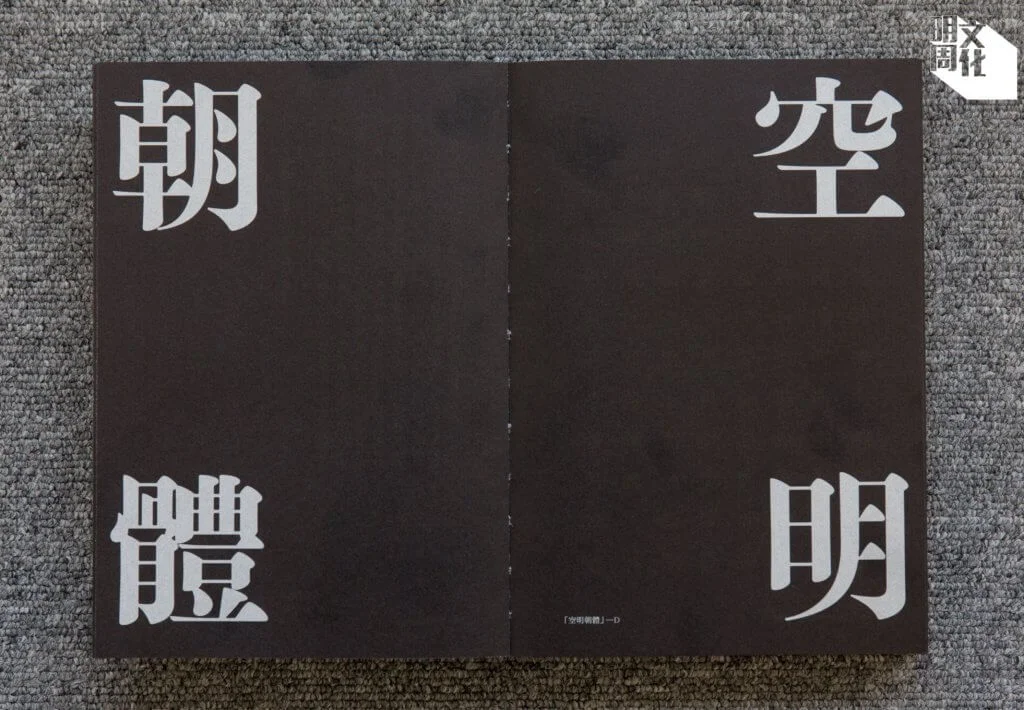
樽頸過後的轉機
然而,許瀚文久久未有將「空明朝體」投入完整生產,補完所有中文基本通用字,讓「空明朝體」可以真正用作正文排版的計劃—直到去年六月。
去年初,他憑着一八年贏得的「DFA 香港青年設計才俊獎」獎學金,到德國設計公司KMS TEAM實習。他離開香港,遠赴慕尼黑的時間,正處於事業的瓶頸。「在這一行,自己不算最後生,作品又不算是最新最fresh的,講老又不夠老資格。雖然做的事很多時近type director的位置,但又未到那個時候。」三十來歲的他,努力十年,漸感迷惘,「夾了在中間,不上不下,所以想試試其他可能性。」
一心想在德國深造,不幸當地爆發疫情,自去年三月起,政府下令封城禁足。實習工作驟然停頓,安困愁城也沒意思,許瀚文意興闌珊,決定返港。這反而帶給他新的轉機。
回港後,聞說昔日共事過、造字資歷逾三十年的造字匠人張堅強和馮景祥,因為Monotype香港分部停業而突然失去工作,「他們一直是中流砥柱,做了很多年,不想他們轉行,失去他們」,因此許瀚文試問兩位前輩:有沒有興趣一起完成整套「空明朝體」?
他不諱言,自己一直未有實現「空明朝體」的構想,是因為自己眼高手低,經驗不足,始終無法把字造得「工整得來,又是活的」;若得兩位造字經驗老到的師傅幫手,定必能夠把「空明朝體」完成。「果然,他們搞了兩個月,事情已經和我想像的一樣,到我最滿意的程度」,他特別感謝張堅強,「阿堅研究書法廿幾年,他可以帶字的氣韻章法等到這套字體。」
「我有idea,然後配合他們的craft,事情就完美了。」他成功突破了瓶頸,找到新的路向。
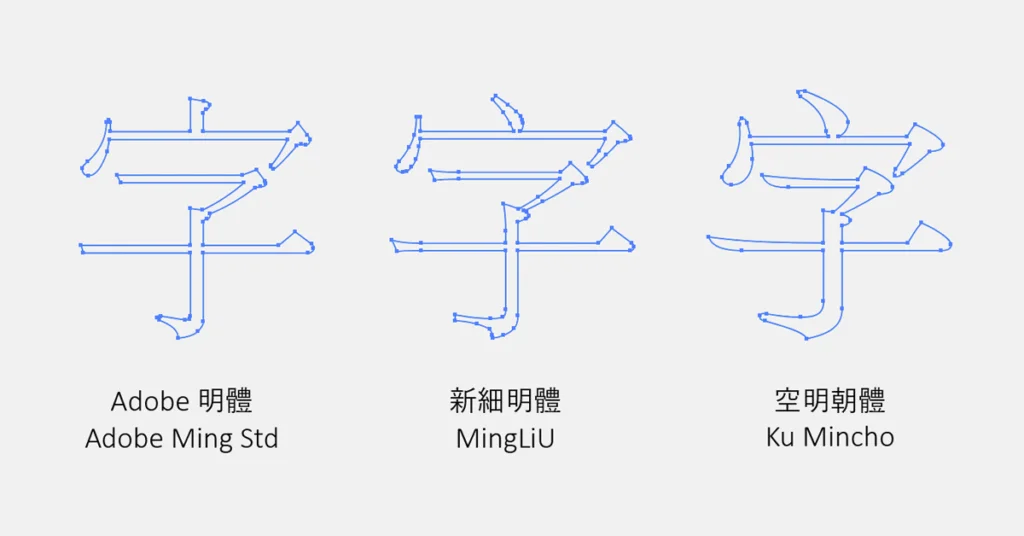
創建空明朝體
事情的確似是完美地向好發展。「空明朝體」集資計劃年初在台灣網絡平台上向羣眾集資,不足一個月,已獲贊助逾千萬台幣,贊助人中八成多來自台灣,餘下是香港人。聶永真、葉忠宜、方序中等著名台灣設計師也推薦「空明朝體」。
「空明朝體」在台灣大受矚目,許瀚文自己分析,原由固然與字體設計近年在台灣漸獲重視,當地設計創作界對新字體的需求有關,但也可能是,「空明朝體」美學符合台灣氣氛。事實上,「空明朝體」原名「台北明體」,字體一方面受台灣溫柔婉轉的民風啟發,另外也受他在台灣故宮參觀時看到明宋古籍裏的古樸字型時的感受所影響。
香港是許瀚文的家,台灣是助「空明朝體」成真的地方。現募得款項,足以支持他及其團隊造好一萬五千字,讓「空明朝體」完整收錄香港、台語及客家語的通用語及拼音,「那香港和台灣的內文字都不會缺字,真的可以用來排書。這是漢字部分的終極目標。」集資計劃二月結束後,團隊三人便會全力開發「空明朝體」,以昔日刻字匠人的技術精神,把每隻中文字精雕細琢逐一造好。計劃訂明,二〇二二年三月基本款的七千六百字就可供下載。許瀚文不敢怠慢了。
他自己也相當期待「空明朝體」完整推出的一天,那時,人們要用中文字體,將會有多一種選擇,也可能帶來新的風氣:「或推動到新的做法,之後新的字體也能多注重呈現中文的美感。有人buy(這個看法),之後都會有人跟。多人跟,最終受益的,都是讀書的人。那真的是推動到變革。」這是一個香港造字人的抱負。